한글폰트 제작 체계를 다 바꿨습니다.
한글폰트를 초성, 중성, 종성 체계의 벌수를 만들어서 조정하던 방식으로 폰트 제작을 했습니다. 기존의 비트맵폰트 제작에 사용하는 방식을 채용하여 작업을 했는데 다시 Fontforge 같은 전용 프로그램으로 확인을 하고 수정할 부분을 가상의 초성, 중성, 종성 심볼을 만들어 필요한 글자를 수정하면 전체가 교정되는 형태 였습니다.
그렇게 하다보니 글자의 모양이 이상한 경우 다시 재작업을 해야하는 경우도 생기고 사람의 글씨는 구조화하면 고유의 글씨 형태를 가질 때 해결하기 어려운 부분이 생깁니다.
캘리그래피 처럼 시그니처같은 글자가 있게 되면 그걸 해결하기 위해 모든 것을 조정해야 합니다. 영문의 필기체와 같이 연결되는 글자를 만들었을 때 자연스럽게 이어지지 않는다는 것입니다.
거의 모든 글자의 유형을 생각해야 하니까 머리가 많이 복잡했는데 이제 어느정도 정리가 되었습니다. 스펜서리안이나 팔머 같은 영문필기체에 힌트를 얻기도 했습니다.
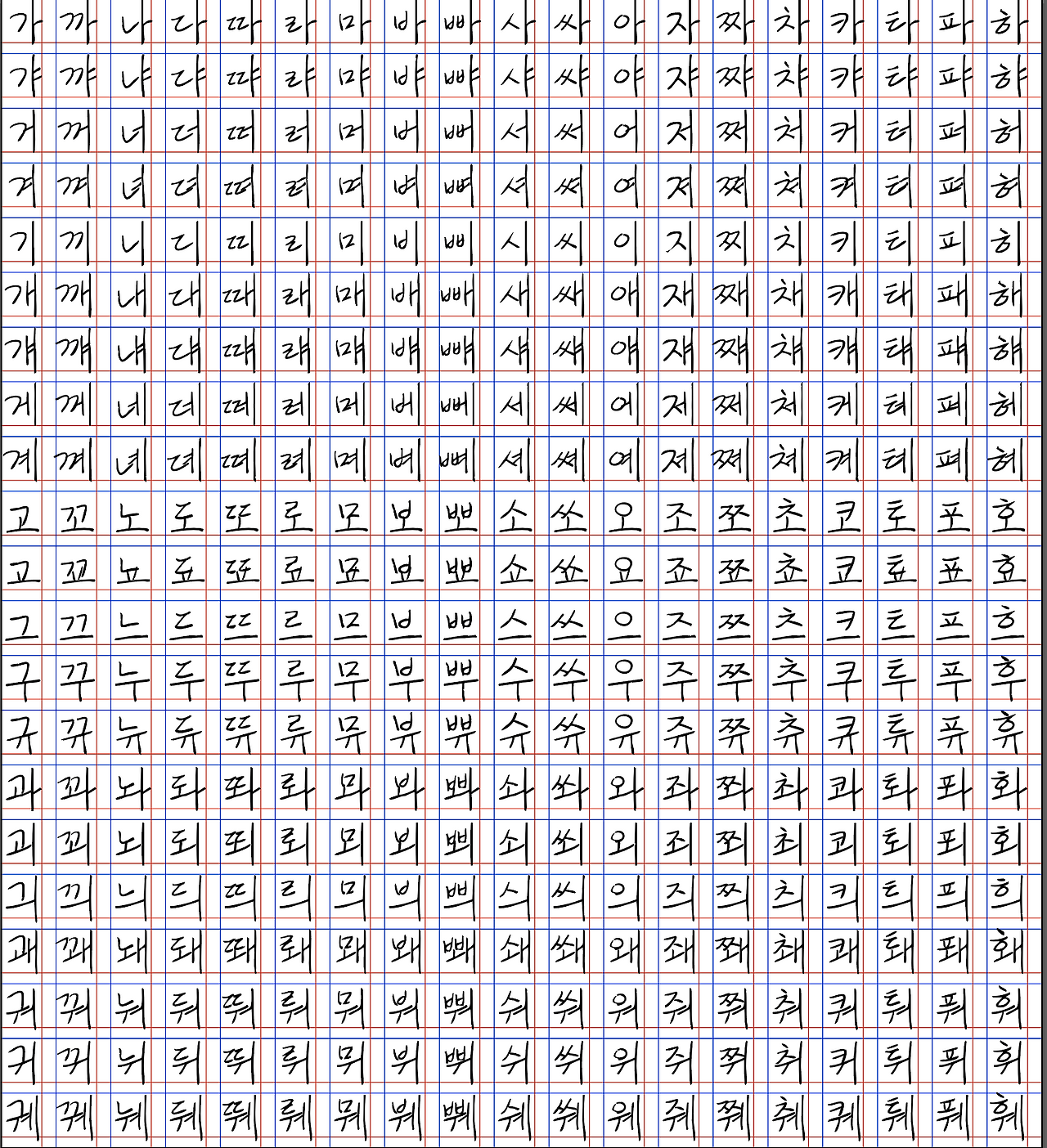
초성, 중성의 조합부분으로 가로, 세로, 그리고 ㅏ에서 ㅖ까지 글자를 가로, 세로 쓴 방향을 모두 동일하게 글자의 균형을 한 번에 잡아둘 수 있습니다. 이 전에 한글 폰트에 관한 천지인 방법론을 적용해서 1세트를 구성했고
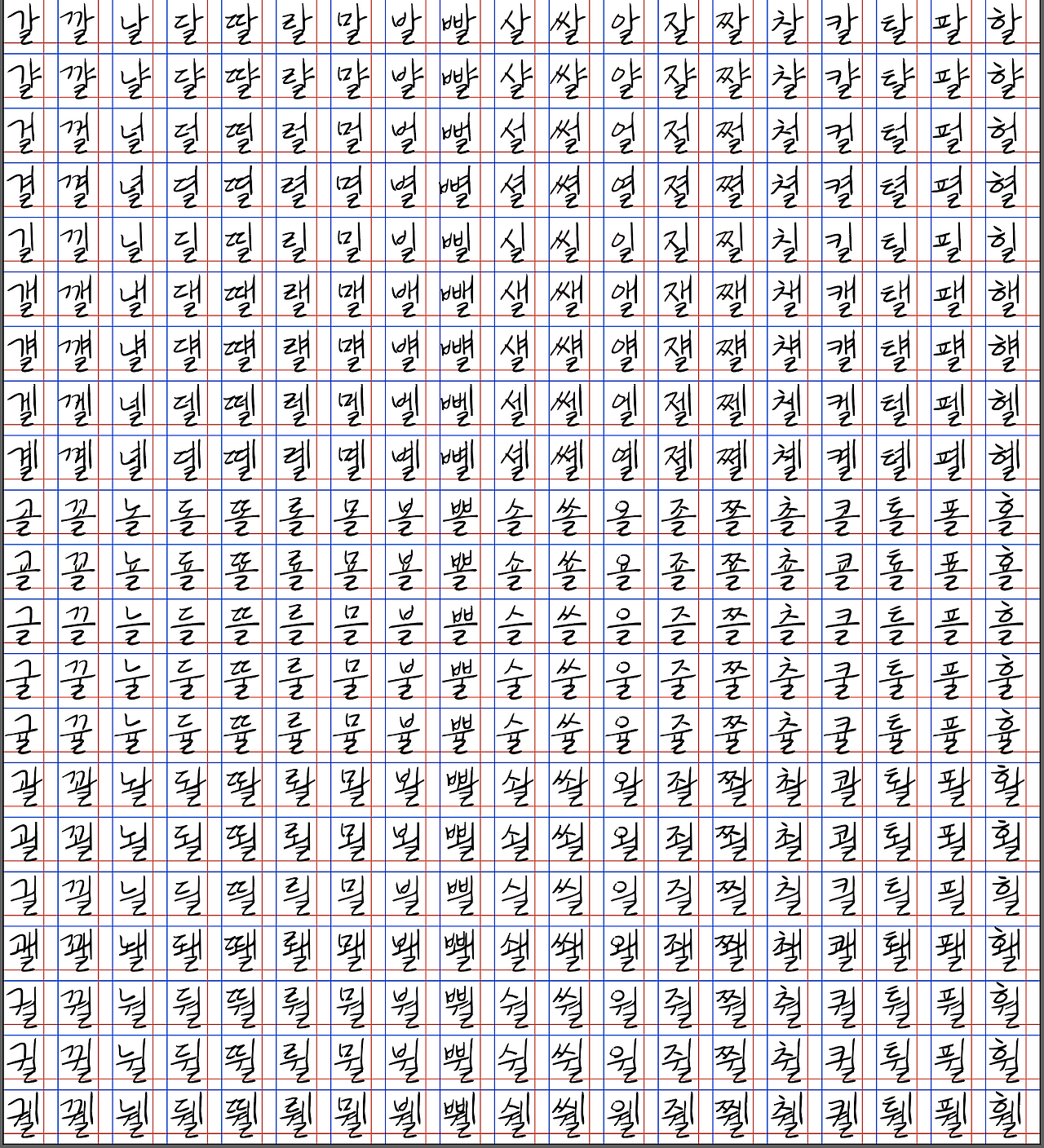
초성+중성+종성(안씀)에 해당하는 부분 1개세트를 추가했으며 이는 종성 ㄹ을 붙여놓은 것은 화면상에서 보기위함이지 실제는 데이터를 추출해서 운영합니다.
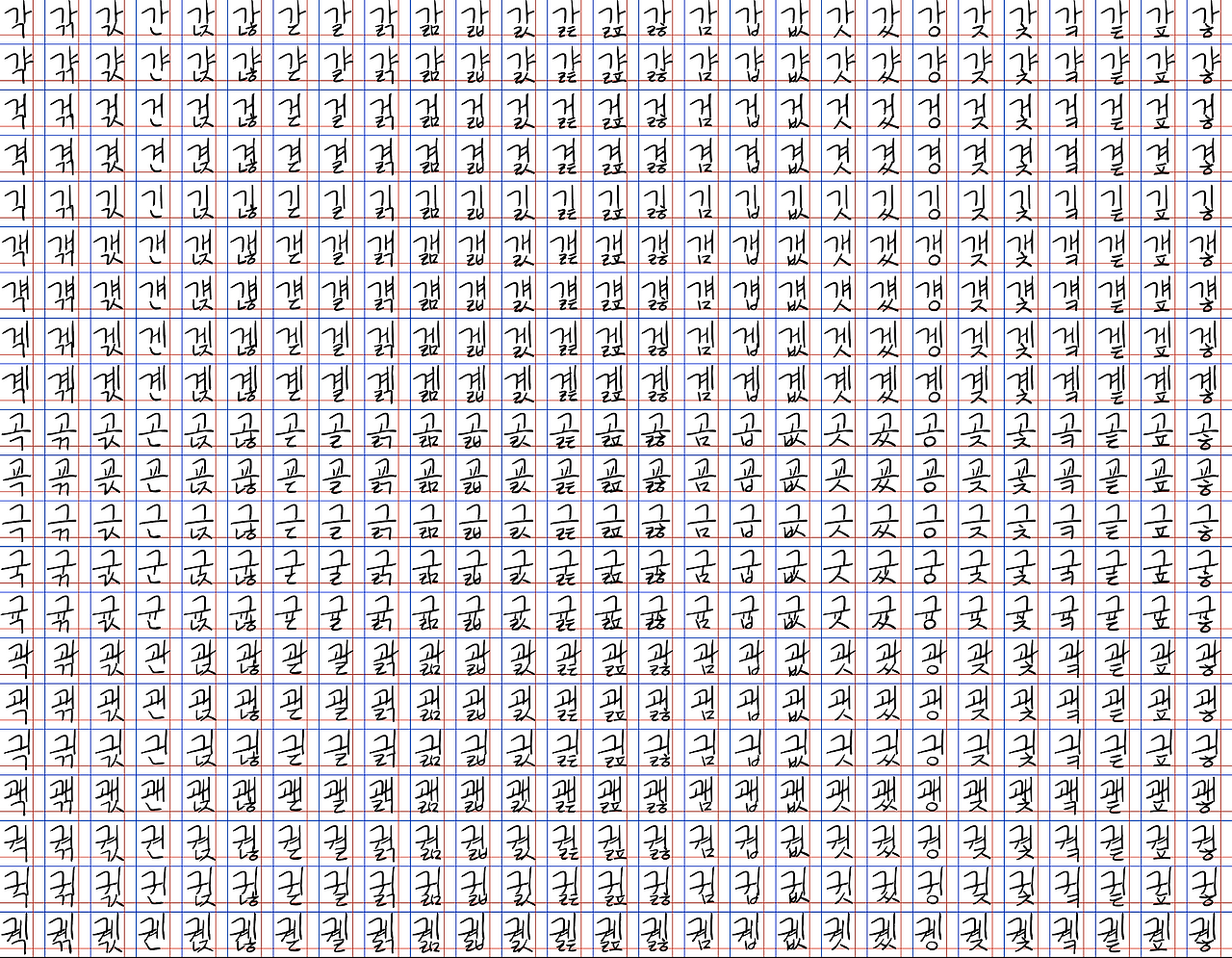
마지막은 종성에 대한 세트로 종성의 위치를 잡아 글자별로 운영하는 것을 화면에서 보면서 작업을 합니다. 화면 상에서는 조금 복잡해 보이지만 사실 저 글자를 쓰는게 아니고 종성의 위치만 보게됩니다.
최종적으로 ttf 파일이 생기며 글자가 들쭉날쭉한 부분을 일괄적으로 편집할 수 있기 때문에 손글씨의 가장 고질적 문제인 가시성, 일관성을 유지하는데 도움이 됩니다.
저희가 이 부분에 대해서 고민하는 이유는 다음번 한자작업을 한 번에 해결하기 위함이며 한자의 부수를 기준으로 폰트 벌수를 줄여서 제작할 수 있기 때문에 보면서 편집할 수 있는 형태로 전환하고 있습니다.
한글폰트 디자이너가 빨리 많아지고 다양한 폰트 제작을 위해 이런 제작 시스템으로 접근하고 있고 디자인 폰트를 얼마나 쉽게 만들 수 있는지 곧 영상으로 제작해보려고 합니다.